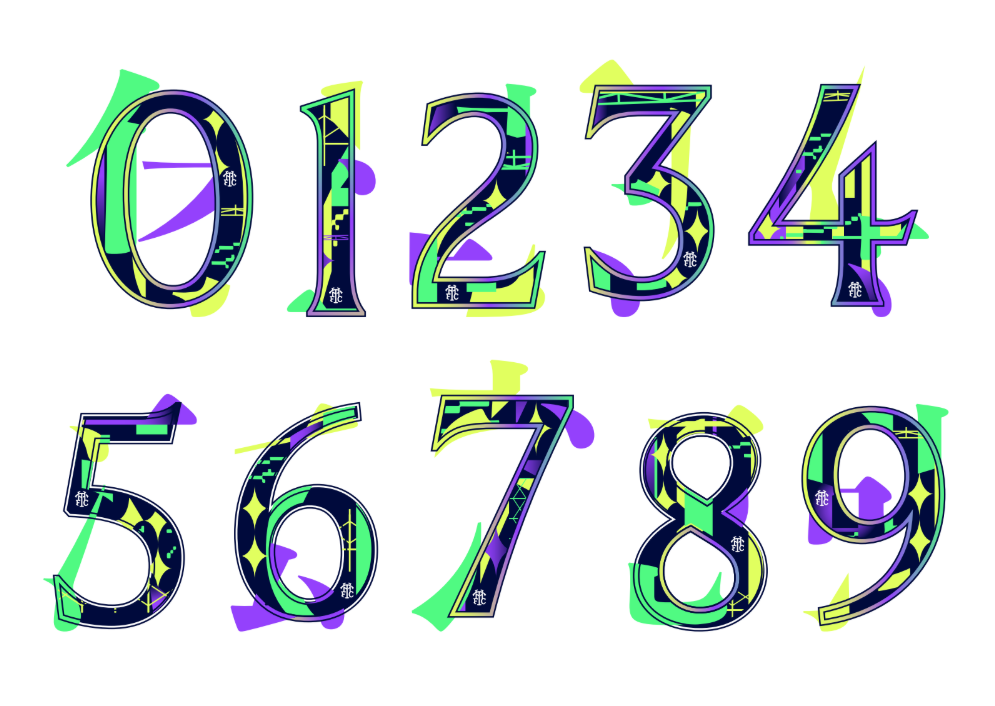
As pré-temporadas na Ásia são conhecidas por trazerem designs únicos e camisas que viram itens de colecionador instantâneos. Com o Tottenham Hotspur, não foi diferente. Para celebrar a passagem dos Spurs pelo oriente em 2025, a Nike apresentou uma tipografia exclusiva, que foge completamente do padrão da Premier League.
Estilo Visual: Fusão Cultural
A fonte do Tottenham Hong Kong Tour 2025 é uma obra de arte à parte. Diferente da fonte sóbria utilizada no Campeonato Inglês, esta versão incorpora elementos estéticos que remetem à caligrafia oriental, com pinceladas dinâmicas e acabamentos angulares.
Ela foi desenhada para se destacar sobre o tecido Dri-FIT da Nike, trazendo uma sensação de movimento e velocidade. É a escolha perfeita para quem quer fugir do óbvio e oferecer uma personalização “Rare Edition” em camisas de futebol.